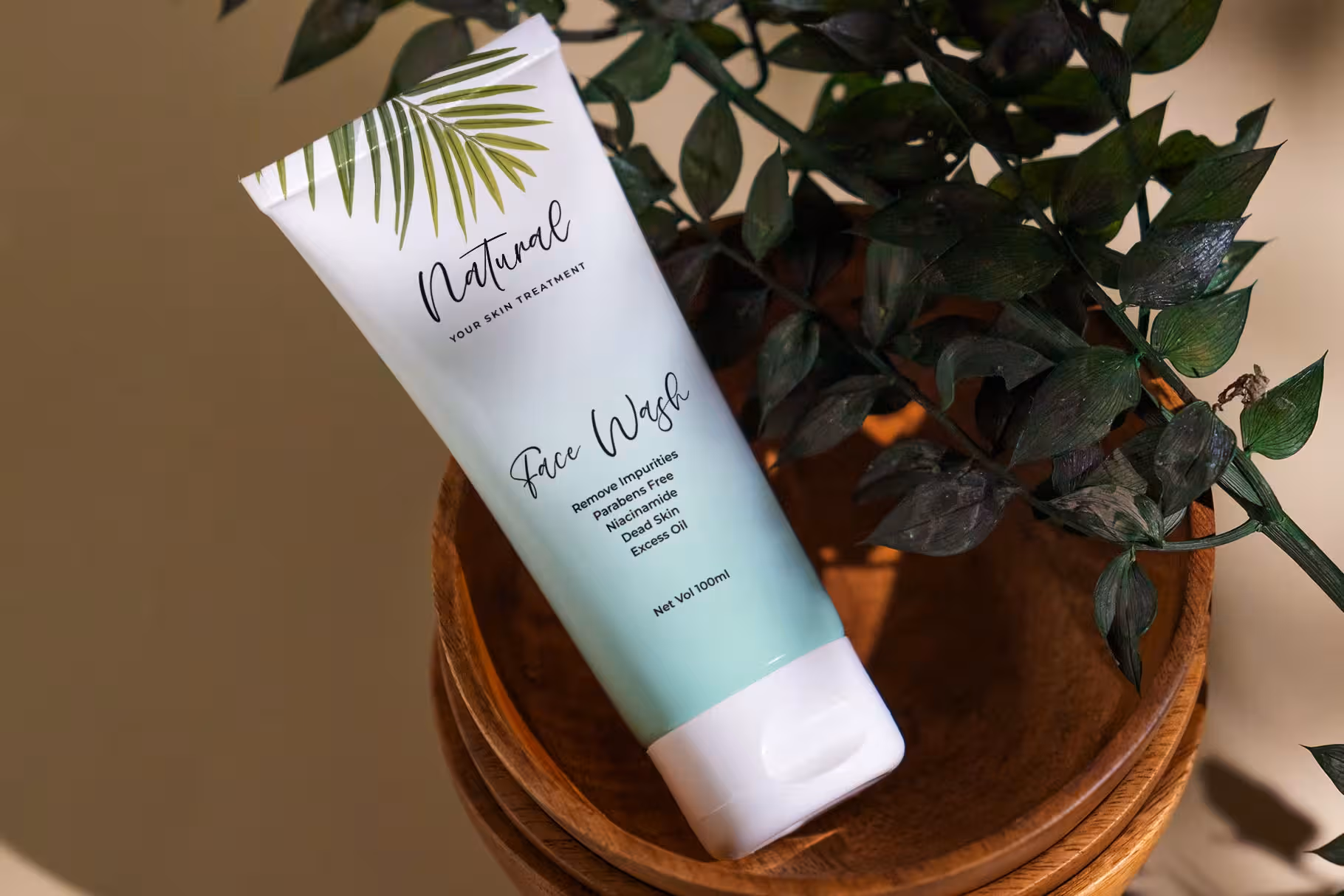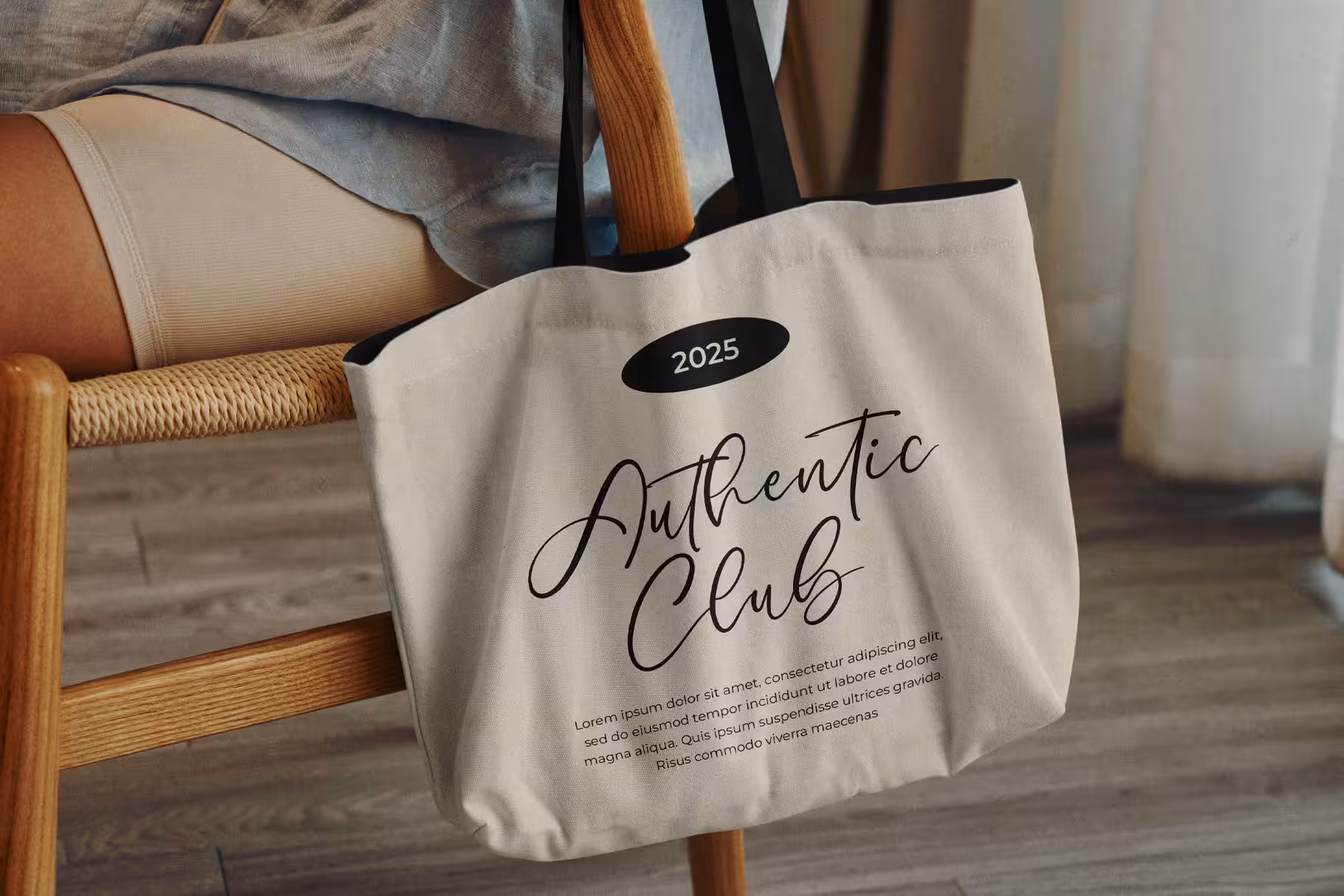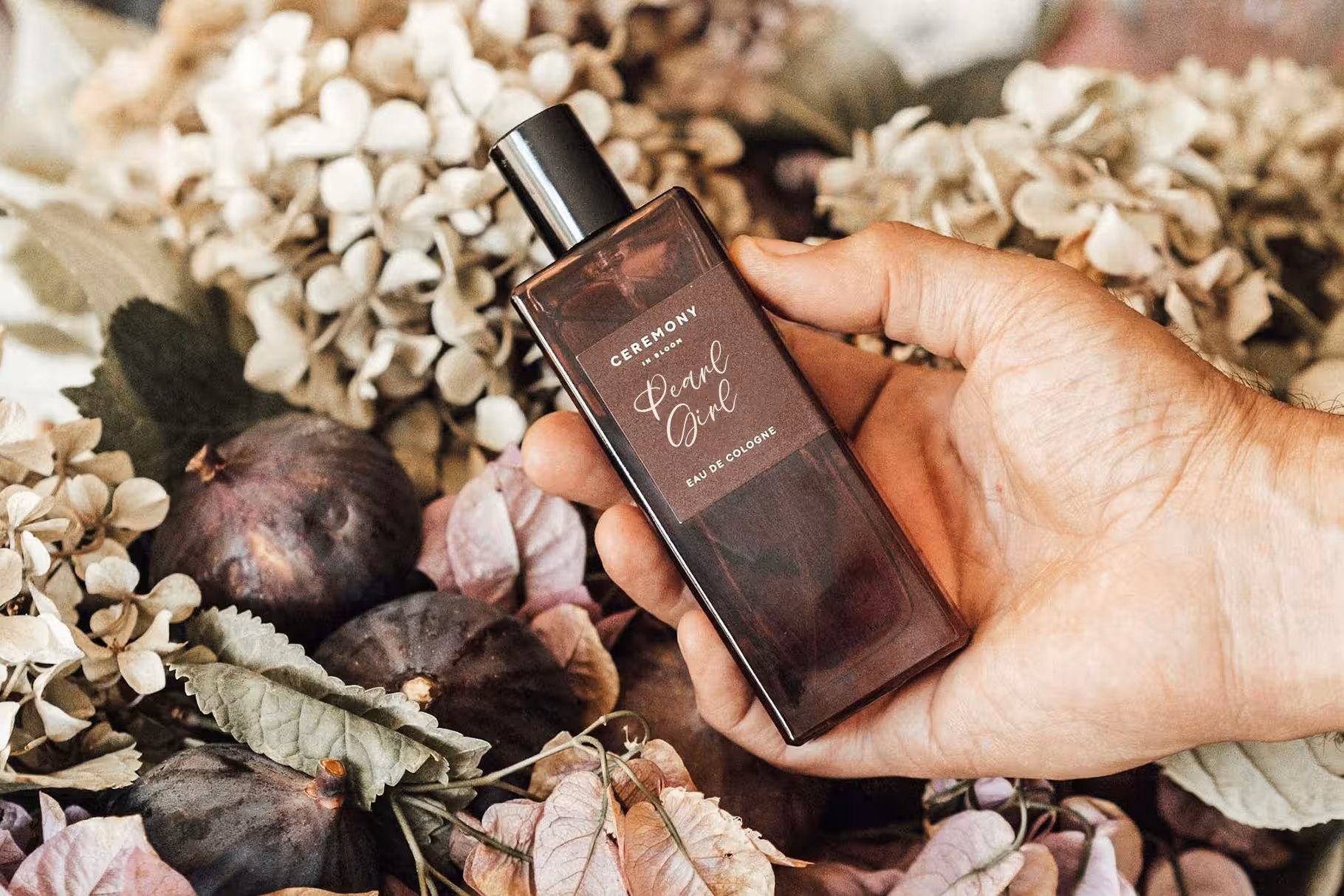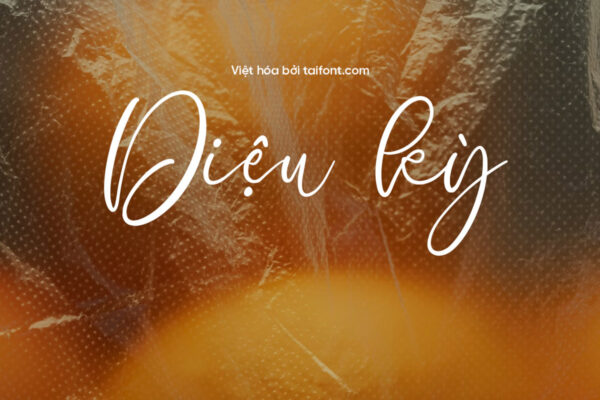
Giới thiệu về Font TF Belasty Việt hóa
TF Belasty Việt hóa là một font chữ viết tay (script font) nổi bật với vẻ đẹp mềm mại, thanh lịch và đầy quyến rũ, lý tưởng để tạo nên sự tinh tế và sang trọng trong các thiết kế. Font này toát lên phong thái nữ tính, uyển chuyển và rất có hồn, gợi cảm giác về sự tỉ mỉ và chăm chút.
Với sự duyên dáng và tính thẩm mỹ cao, Belasty là lựa chọn hoàn hảo cho các ấn phẩm cần truyền tải vẻ đẹp, phong cách và sự tinh tế, đặc biệt là trong ngành mỹ phẩm:
- Thiết kế mỹ phẩm: Hoàn hảo để sử dụng trên bao bì sản phẩm, nhãn mác, catalogue, hoặc các chiến dịch marketing của các thương hiệu mỹ phẩm. Font này giúp khẳng định chất lượng, sự sang trọng và vẻ đẹp tự nhiên của sản phẩm, thu hút ánh nhìn của khách hàng và truyền tải thông điệp về sự tinh khiết, mềm mại.
- Thiết kế thời trang (nữ tính): Phù hợp cho các thương hiệu thời trang nữ, đặc biệt là những bộ sưu tập mang phong cách thanh lịch, lãng mạn. Font có thể dùng trên nhãn mác, lookbook, hoặc các ấn phẩm quảng bá.
- Thiết kế thiệp và thư mời: Mang lại vẻ đẹp trang trọng, cá nhân hóa và đầy cảm xúc cho những tấm thiệp mời sự kiện, thiệp chúc mừng hoặc thư cảm ơn.
Với TF Belasty Việt hóa, bạn có thể dễ dàng thổi hồn nữ tính, sự tinh tế và sang trọng vào các thiết kế, tạo ra những sản phẩm không chỉ đẹp mắt mà còn đầy cảm xúc và sức hút đặc biệt, nhất là đối với phái đẹp.